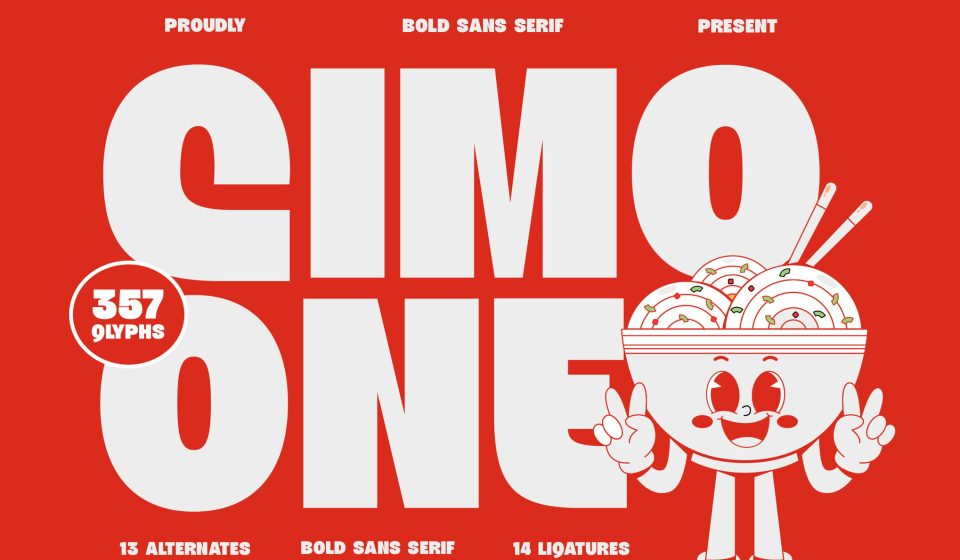
با فونت Cimone One، قدرت و مهربانی را در طراحیهای خود ترکیب کنید
تایپفیسی با فرمهای ضخیم و لبههای نرم برای تاثیرگذاری حداکثری 🎨
فونت Cimone One یک فونت نمایشی (Display) در سبک سانسریف بولد است که با حروف سنگین، فشرده و شخصیتی پرانرژی طراحی شده است. این تایپفیس “چاق و چله” (Chunky) برای ایجاد بیشترین تاثیر بصری ساخته شده و انتخابی ایدهآل برای پوسترهایی است که باید از راه دور جلب توجه کنند. لبههای گرد و فرمهای دوستانه آن باعث میشود که طرح شما در عین داشتن حضور گرافیکی قوی، بسیار صمیمی و دردسترس به نظر برسد.
انعطافپذیری بالا در طراحی با حروف جایگزین و لیگاتورها
چیزی که Cimone One را از یک فونت بولد ساده متمایز میکند، وجود ۱۴ لیگاتور (حروف ترکیبی) و ۱۳ حرف جایگزین (Alternates) است. این ویژگیها به طراحان اجازه میدهد تا ترکیببندیهای اکسپرسیو، عناوین استایلبندی شده و کانسپتهای لوگوی منحصربهفردی را خلق کنند. با وجود ۳۵۷ گلیف مختلف، دست شما برای خلق تایپوگرافیهای خاص کاملاً باز است. ✨
ویژگیهای کلیدی و فنی فونت Cimone One:
- استایل Bold & Chunky: ضخامت بالای حروف که وضوح و قدرت تیترهای شما را تضمین میکند.
- طراحی مهربان و زنده: لبههای گرد که حس مثبت و شادی را به مخاطب منتقل میکند. 🛠️
- مجموعه کامل کاراکترها: شامل حروف بزرگ و کوچک، اعداد و علائم نگارشی. 🖋️
کاربردهای پیشنهادی برای فونت Cimone One:
این فونت در حوزههایی که نیاز به Visual Punch دارند، میدرخشد:
- برندینگ مواد غذایی: طراحی لوگو و بستهبندی محصولات خوراکی و کافهها. 🍔
- محصولات کودکان: انتخابی عالی برای اسباببازیها، کتابهای داستان و پوشاک کودک.
- شبکههای اجتماعی و تبلیغات: ساخت کاورهای اینستاگرام و یوتیوب با انرژی بالا. 📱
- طراحی محصولات (Merchandise): چاپ روی تیشرت، ماگ و استیکرهای فانتزی. 🎁
چرا Cimone One را به جعبهابزار خود اضافه کنیم؟
فونت Cimone One توازنی میان سادگیِ مدرن و شخصیتِ بازیگوش برقرار کرده است. خطوط ضخیم و ساختار تمیز آن باعث میشود تا در پسزمینههای شلوغ هم به خوبی خوانده شود. اگر به دنبال فونتی هستید که “صدای بلندی” داشته باشد اما در عین حال لبخند بر لب مخاطب بنشاند، Cimone One قطعه گمسده پازل شماست. 🚀